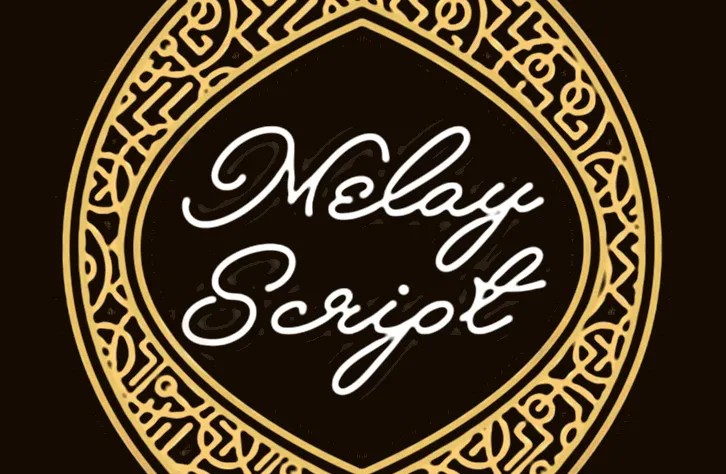
A fonte Melay Script é uma elegante escolha para quem busca expressar seu design com mão escrita delicada e envolvente. Criada por Hamilton, essa fonte tem um carácter natural que evoca momentos de relaxamento e criatividade, especialmente em projetos digitais que buscam manter um tom agradável e familiar. Com uma aparência suave e fluida, Melay Script destaca-se nas categorias de letras cursivas. Seu design permite uma boa legibilidade e ajuda a criar textos com características distintas, ideal para títulos e capítulos de páginas web ou design gráfico. Visite o site da Mans Greback (http://www.mansgreback.com/melay-script) para adquirir sua própria licença comercial.